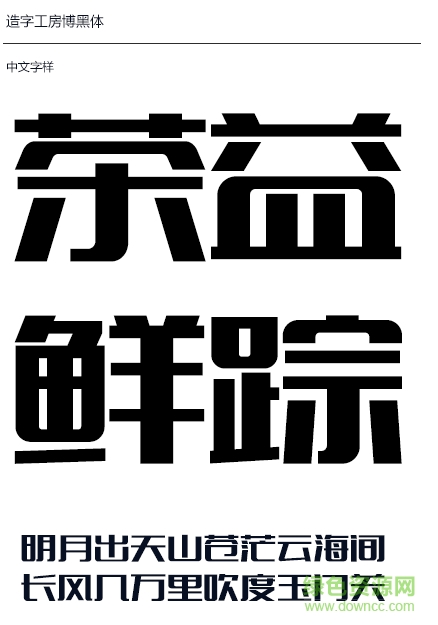
2016造字工房新字體打包是最新的造字工房新字體大全,一共有10款,分別是造字工房致黑體、造字工房堅黑體、造字工房可可體等等,喜歡造字工房字體的趕緊下載吧。
1.造字工房致黑體
造字工房致黑體,字形結構嚴謹而疏朗、形疏而氣緊,橫平豎直的筆畫中加入弧度的處理,剛正而不失盈潤,局部筆畫加入了尖突的效果,讓字形更顯英朗氣質。此款字體適用于報刊雜志及書籍、畫報的主副標題和個性品牌設計推廣等環(huán)境。
2.造字工房明黑體
造字工房明黑體字形扁平,筆畫清晰而飽滿,厚重工穩(wěn),遒勁有力,剛毅而不失俊朗,且直角的處理更顯剛毅,有極強的視覺表現(xiàn)力。此款字體適用于主副標題,有著較大范圍的應用空間。
3.造字工房童心體
造字工房童心體,童趣盎然、個性強烈,字形有著濃郁詼諧可愛的氣息、其筆畫的穿插生動、粗細形態(tài)肆意多變、欹正呼應、給人活潑而不失穩(wěn)重之感,大氣而靈動。口和撇的圓潤處理讓字形更加個性鮮明,生動有趣,有著很強的視覺表現(xiàn)力。適用于大標題及個性品牌設計推廣等環(huán)境。
4.造字工房佳黑體
造字工房佳黑體,其字形瘦長,瘦勁而不失蘊藉、厚重之感,筆畫轉折處做倒角處理,特點鮮明,結構嚴整、剛勁。此款字體適用于科技產(chǎn)品及競技視覺環(huán)境中。
5.造字工房堅黑體
造字工房堅黑體,結構端正、字形飽滿、筆畫勻稱,字形整體風格剛勁有力而不失俊儒之風,其筆畫中蘊含古樸沉厚端凝之勢。在主副標題與品牌宣傳上有很大的應用空間。
6.造字工房妙妙體
造字工房妙妙體,字形活潑、飄逸靈動、端秀清新、特點明確,撇、捺、點、勾大范圍的弧度增加筆畫的流暢性。捺與鉤上特點的添加與橫豎筆畫特點相互呼應,加上結構的細膩處理使字形更顯俊美挺秀之氣。具有極強的時尚感。此款字體適用于文字標題、廣告設計、企業(yè)宣傳等視覺環(huán)境,有著極強的應用空間。
7.造字工房凌黑體
造字工房凌黑體字形飽滿、整體風格粗曠厚重,字重渾厚、棱角分明,結構方正沉穩(wěn)不失時代氣息,橫的切角處理讓字體更顯剛毅。筆畫與筆畫間的斷層處理,使其筆畫頓挫有力、峻拔剛斷、有抑揚頓挫之感。給整體字形帶來很強的現(xiàn)代科技感。此款字體適用于科技競技環(huán)境中,具有較大范圍的應用空間。
8.造字工房可可體
造字工房可可體,設計師在此款字體筆畫上做了大膽的嘗試創(chuàng)新,在保持整體風格中大膽變幻、勢合形離。筆畫渾圓淳和 、內蓄勁力。口部分筆畫的斷開更加凸顯字體的風格特點。點線面的穿插、像一首有節(jié)奏的樂章、起承轉合恰到好處,活潑而飽滿。此款字體適用于主副標題及個性品牌的設計中。
9.造字工房靜黑體
造字工房靜黑體常規(guī)體 造字工房靜黑體,其字形扁平,此款字體在黑體字形基礎之上巧妙創(chuàng)新,筆畫纖細、簡潔有力、字形簡約、風格明顯且易于閱讀。結構清晰緊密而內斂,給人清新脫俗之感。適用于文字標題、廣告設計乃至正文等視覺環(huán)境,有著極強的應用空間。
10.造字工房博黑體
造字工房博黑體,整體字形風格厚重沉穩(wěn)、制作采用偏上的中宮方式,使其字形方挺規(guī)整,主副筆畫處理清晰明確,筆畫大小極變、輕重有節(jié)、直角和圓角處理穿插,剛柔并濟,有沉穩(wěn)雍容的靜意之美,具有極強的時尚感。此款字體適用于文字標題、廣告設計、企業(yè)宣傳及時尚品牌的設計應用,有著極強的應用空間。